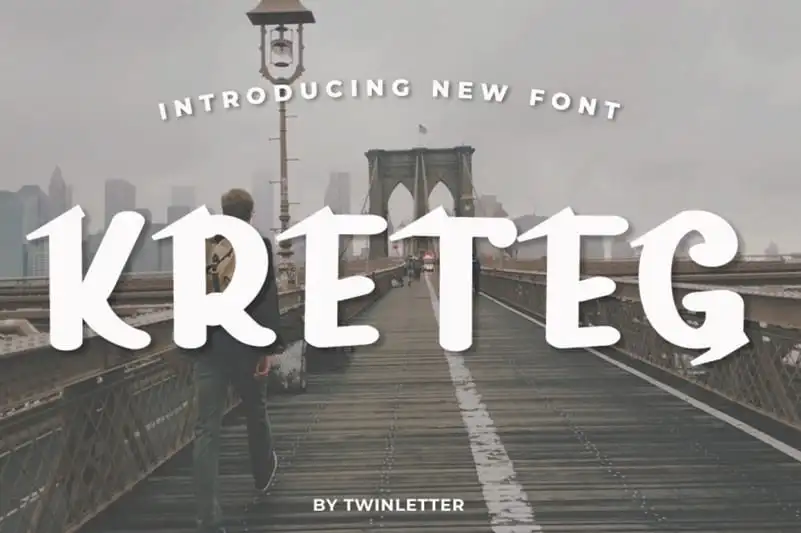
Kreteg Display Font – Download Grátis
Kreteg Display Font é uma fonte de destaque com traços grossos, cuidadosamente entalhada para se tornar uma verdadeira preferência. Suas características casual e encantadoras fazem parecer muito natural e legível, mas também versátil o suficiente para atender a um amplo espectro de aplicações. Com seu charme informal, Kreteg brilha em qualquer contexto, seja usado nas superfícies cheias de atividades ou como uma grande letra no topo de uma página. Seja ela um detalhe suave na frente do design ou o centro de toda a atenção com sua mensagem poderosa, Kreteg é definitivamente uma fonte que deve ser explorada e experimentada.